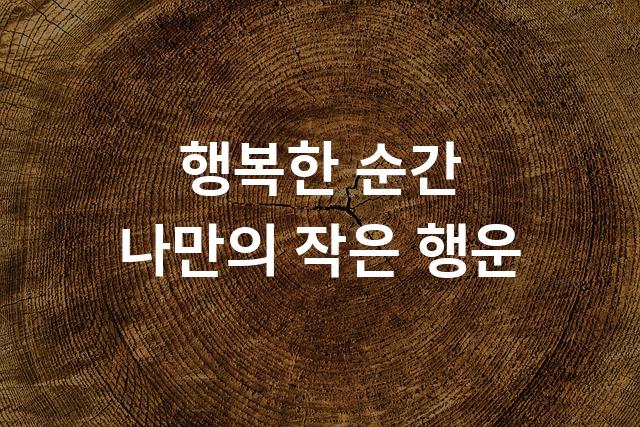
해피니스 산스 Title은 현대백화점에서 제작한 기본 고딕 스타일의 폰트로, 강렬하면서도 깔끔한 인상을 주는 제목용 폰트입니다. 선명하고 간결한 선으로 구성되어 현대적 느낌을 강조합니다.
해피니스 산스 Title은(는)
기본 고딕, 감성적인, 부드러움, 길고/크고 계열의 생김새를 가지고 있으며
인사말 카드, 카페 메뉴, 소셜 미디어 등에서 자주 활용되며, 효과적인 메시지 전달에 적합합니다.
이 폰트는 음식/식음료, 라이프스타일, 이벤트/웨딩 분야에 잘 어울리며,
따뜻한, 귀여운, 편안한 느낌을 담고 있는 것이 특징입니다.
이 폰트와 유사한 폰트로는 나눔고딕, 말리부, 로보토, 스포카 한 산스, 고딕A1 등이 있어요. 함께 비교해 보시면 좋습니다!